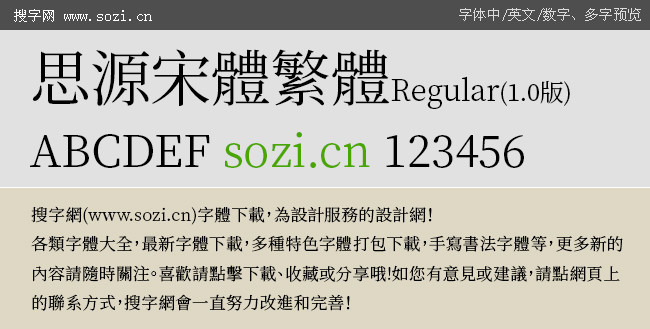
思源宋體繁體Regular
搜字網(wǎng)提供一款思源宋體繁體Regular中文字體下載,思源宋體是一款由谷歌聯(lián)合Adobe發(fā)布全新開(kāi)源字體,是一款免費(fèi)、開(kāi)源宋體字體。有 65535 個(gè)字形,可共同呈現(xiàn)一致的視覺(jué)美感。Regular是一款偏細(xì)的字重,適用于書(shū)籍排版、報(bào)紙排版、畫(huà)冊(cè)設(shè)計(jì),網(wǎng)頁(yè)設(shè)計(jì)等應(yīng)用。
• 風(fēng)格類(lèi)別: 宋體